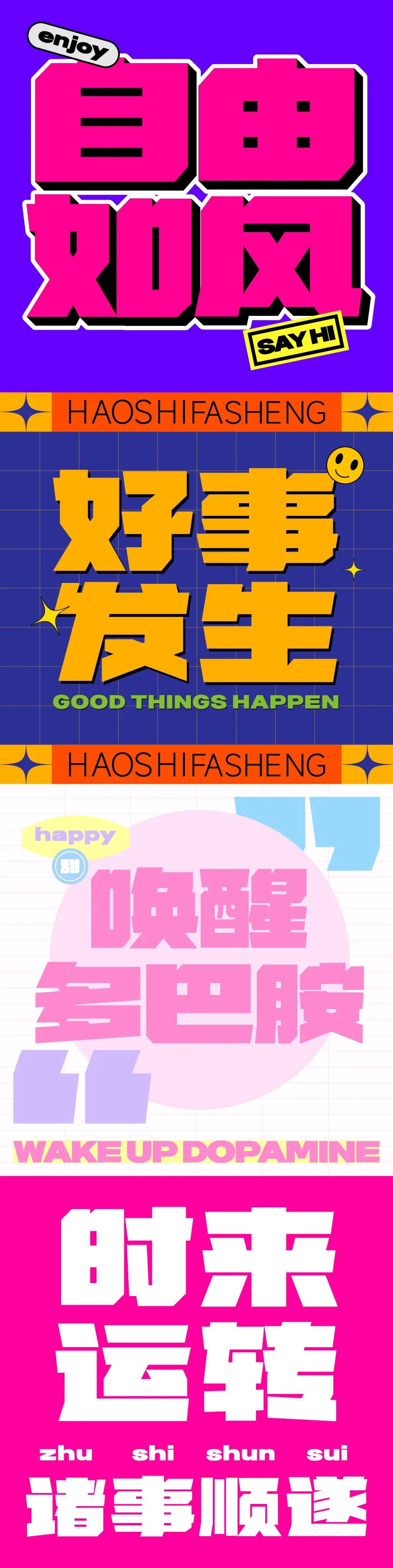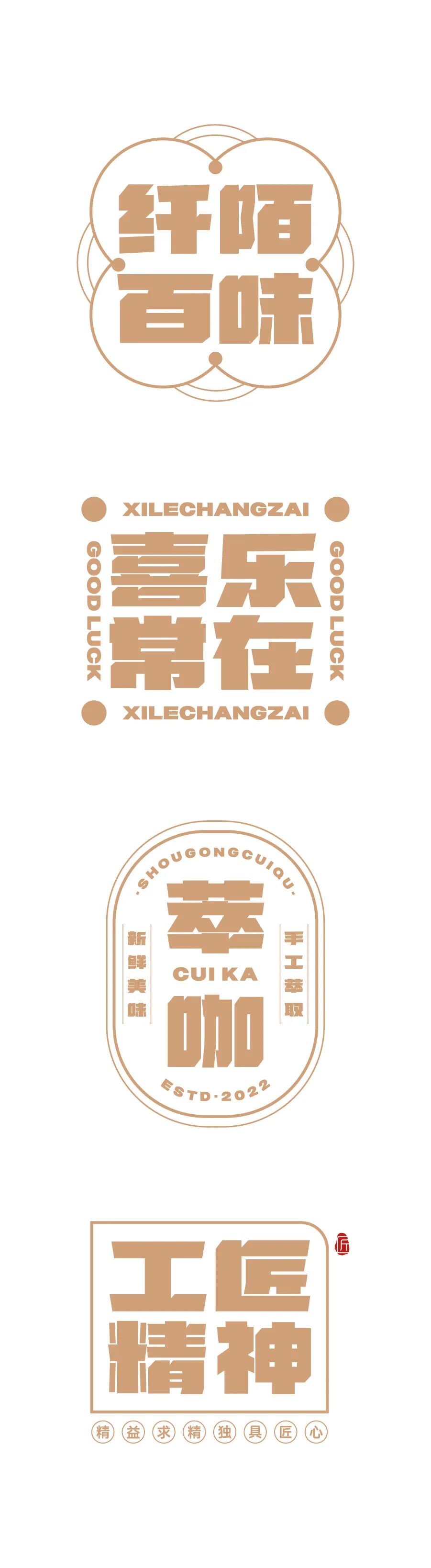
兵克创想黑
兵克创想黑,兵克创想黑,字形厚重,笔画均匀饱满,结构规整,线条干脆利落,转折处多为硬朗的直角或清晰的棱角,强化鲜明的力量特征。字体注重通过字形传递强烈的视觉冲击力,适用于海报、宣传物料、品牌关键信息展示等场景,适合作为主标题或关键信息载体,凸显内容的重点与视觉张力,强化内容的号召力和感染力。